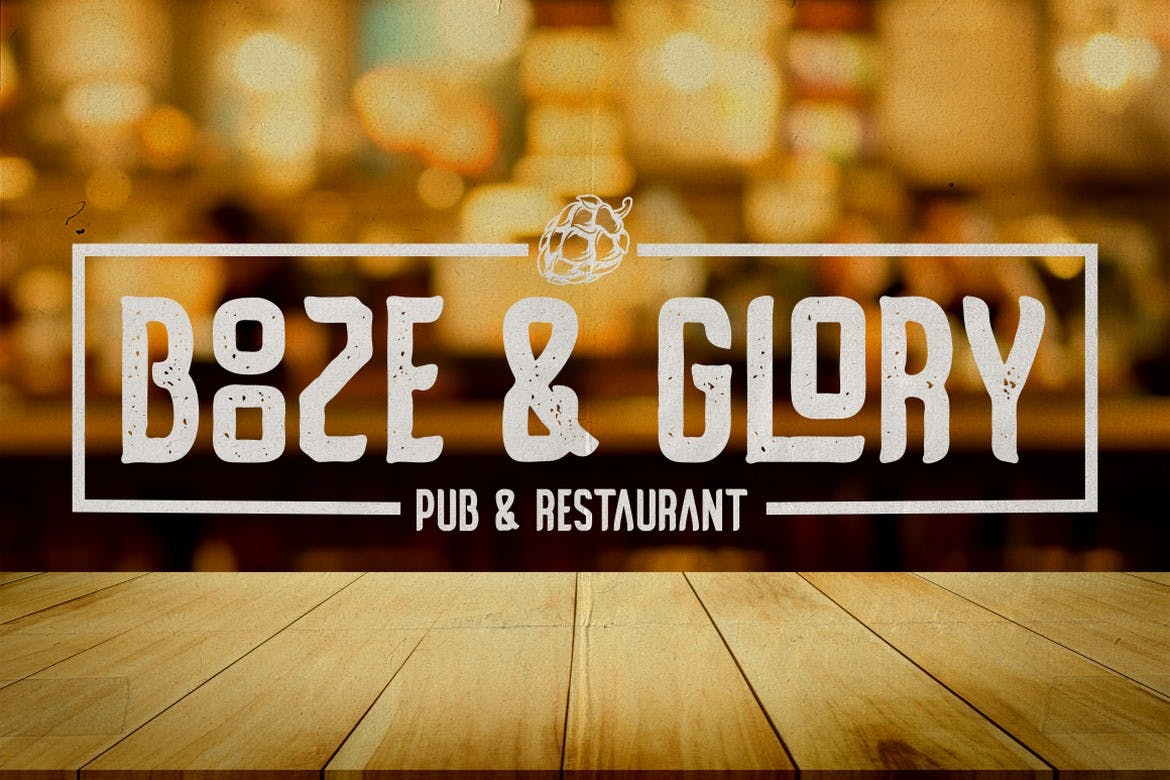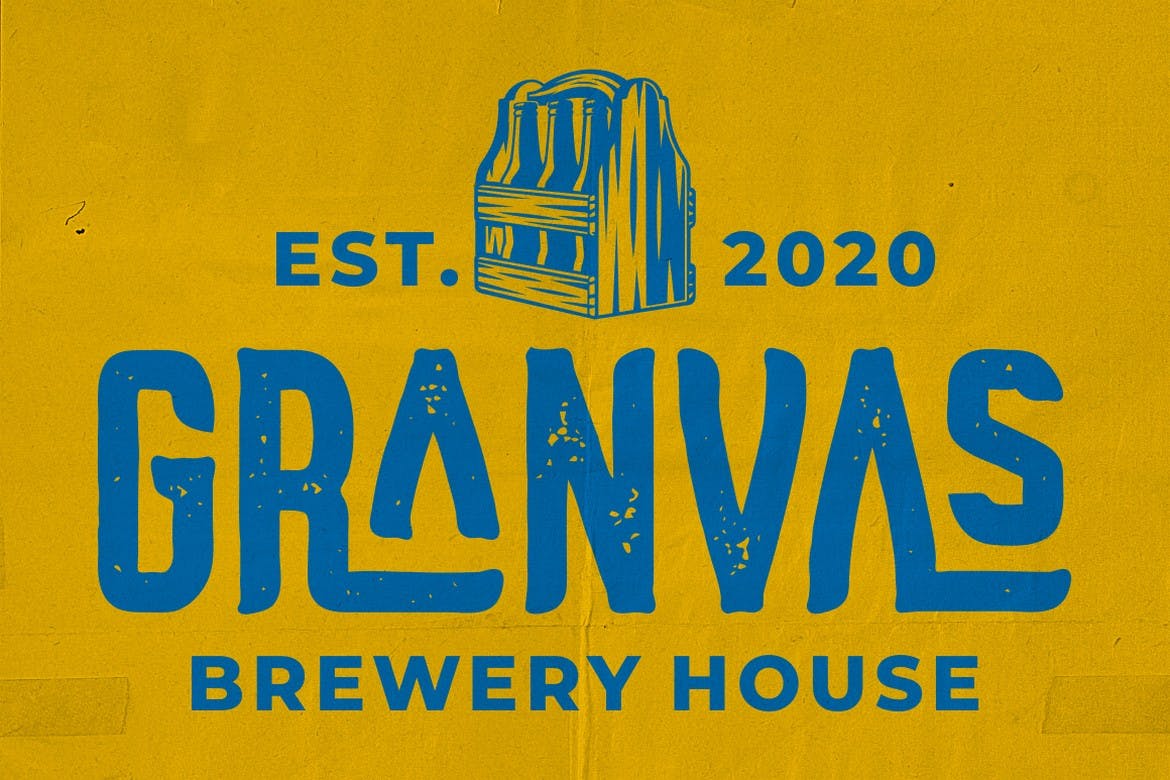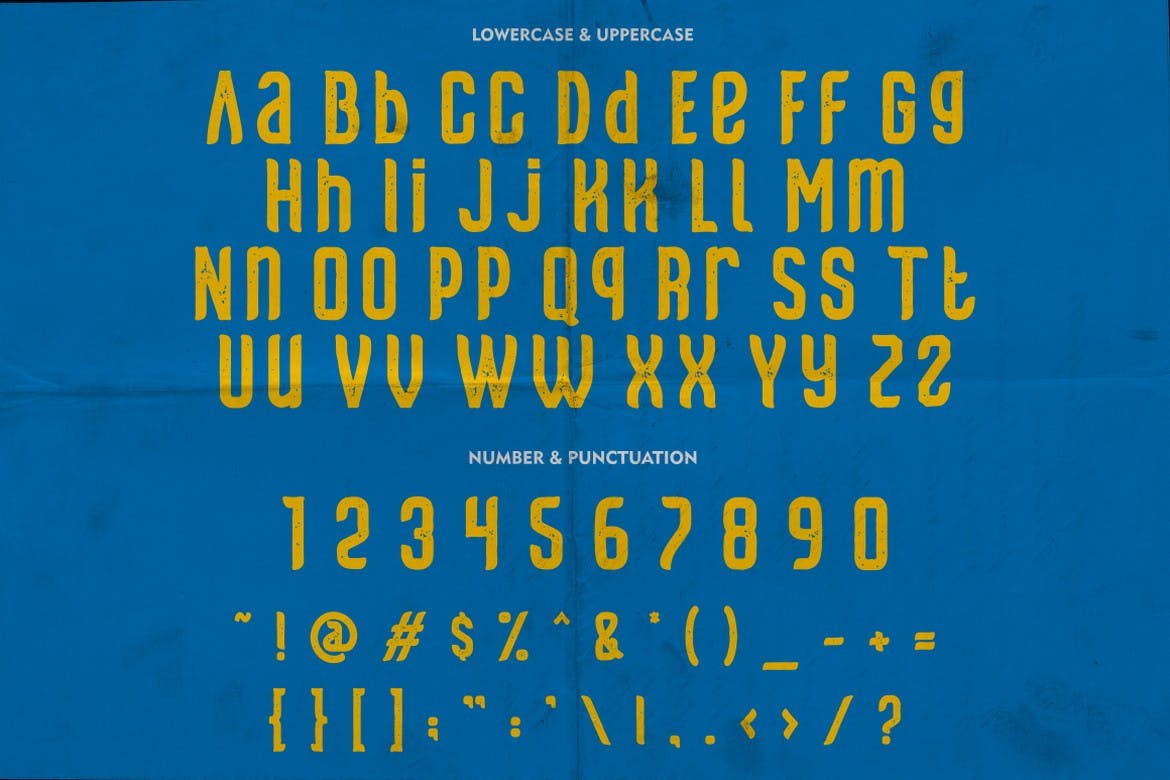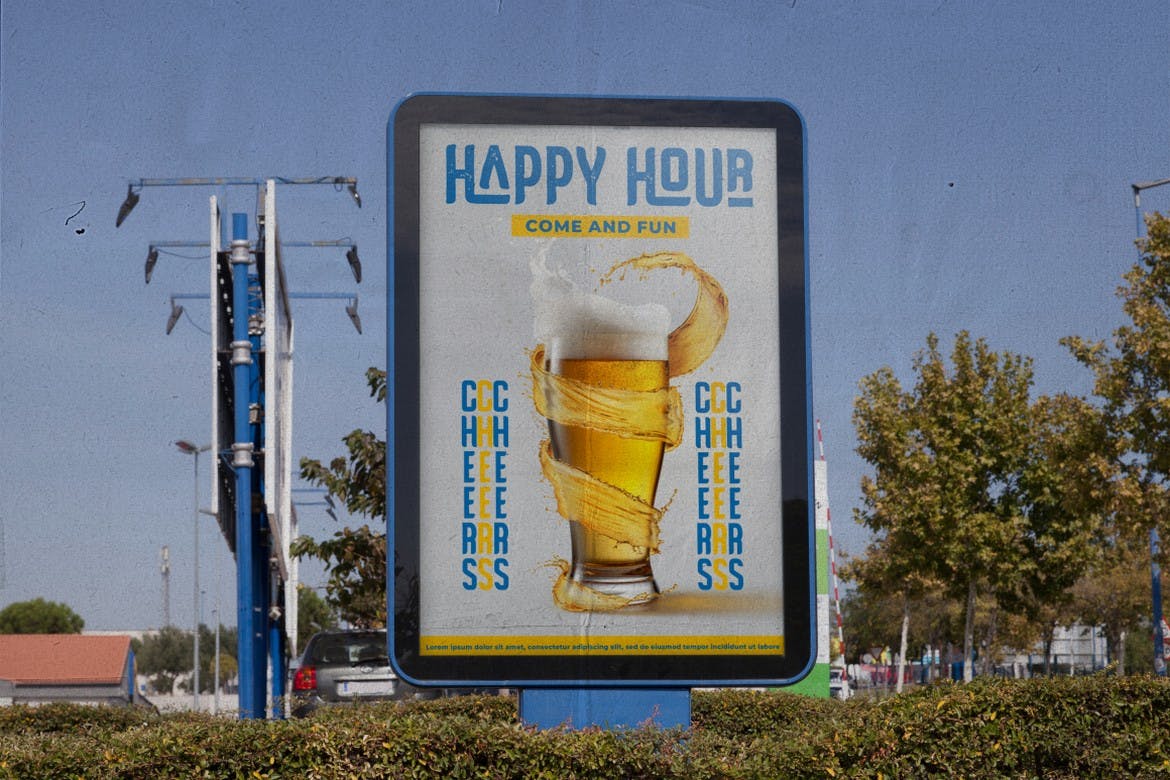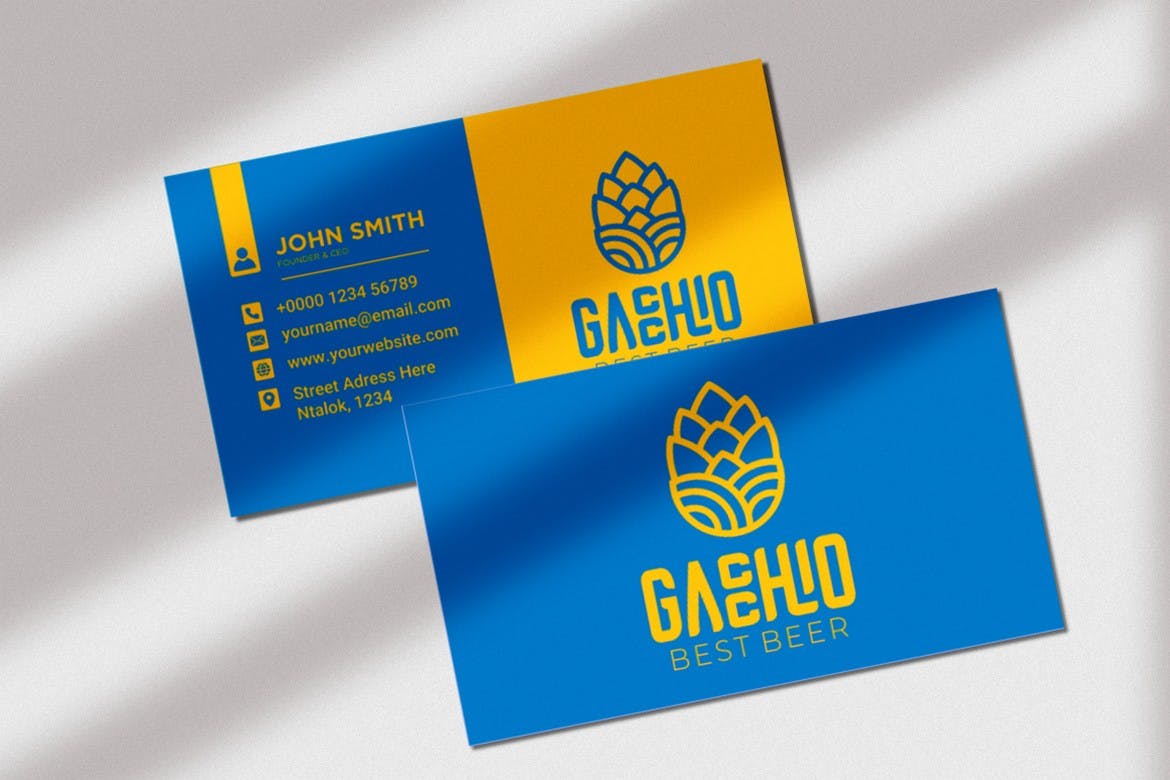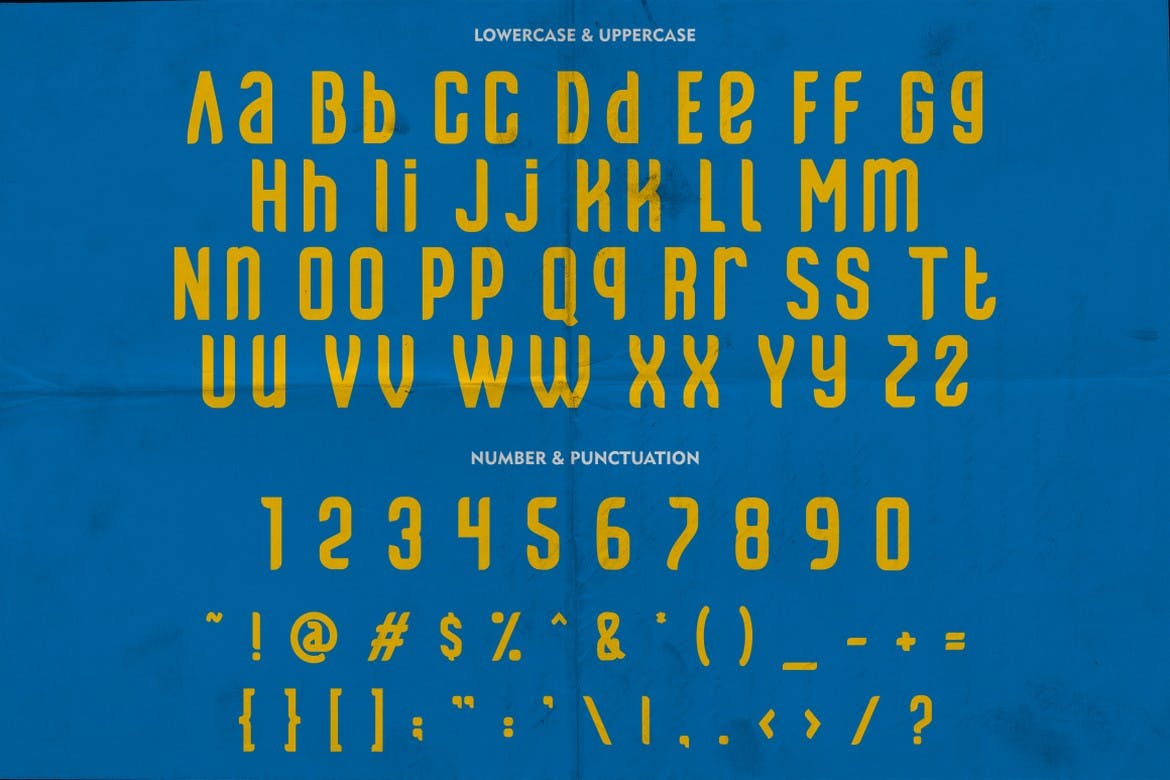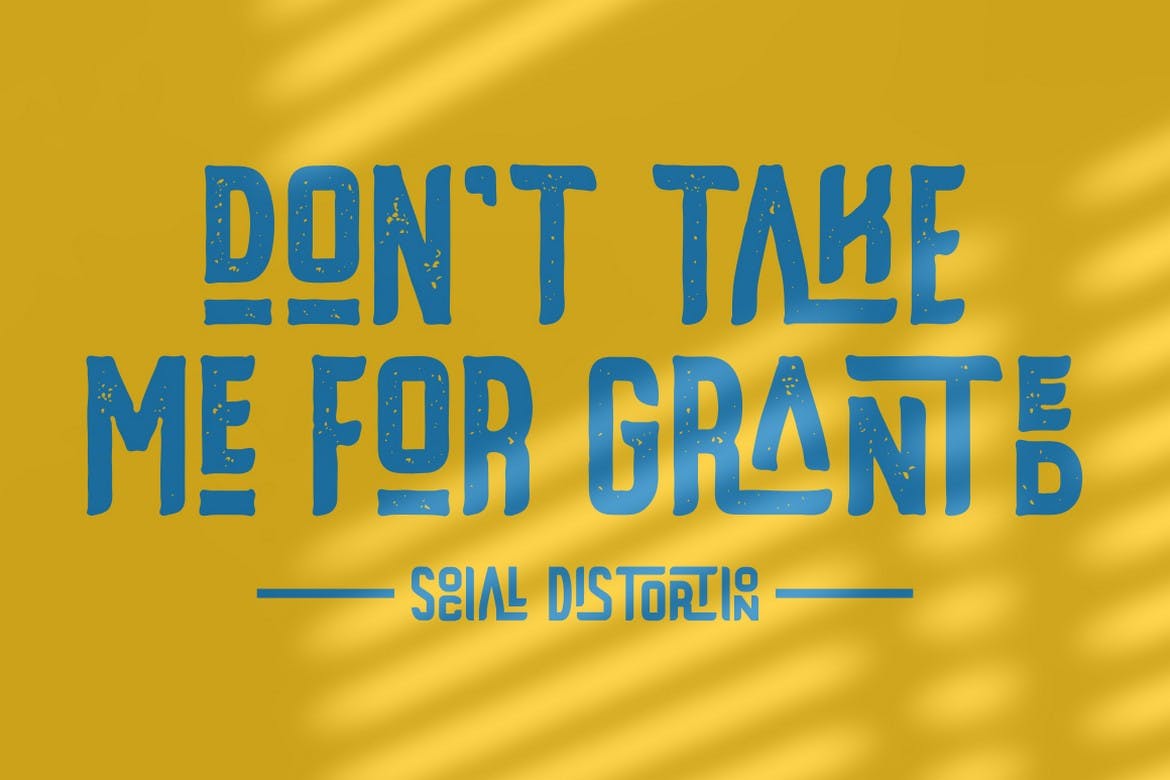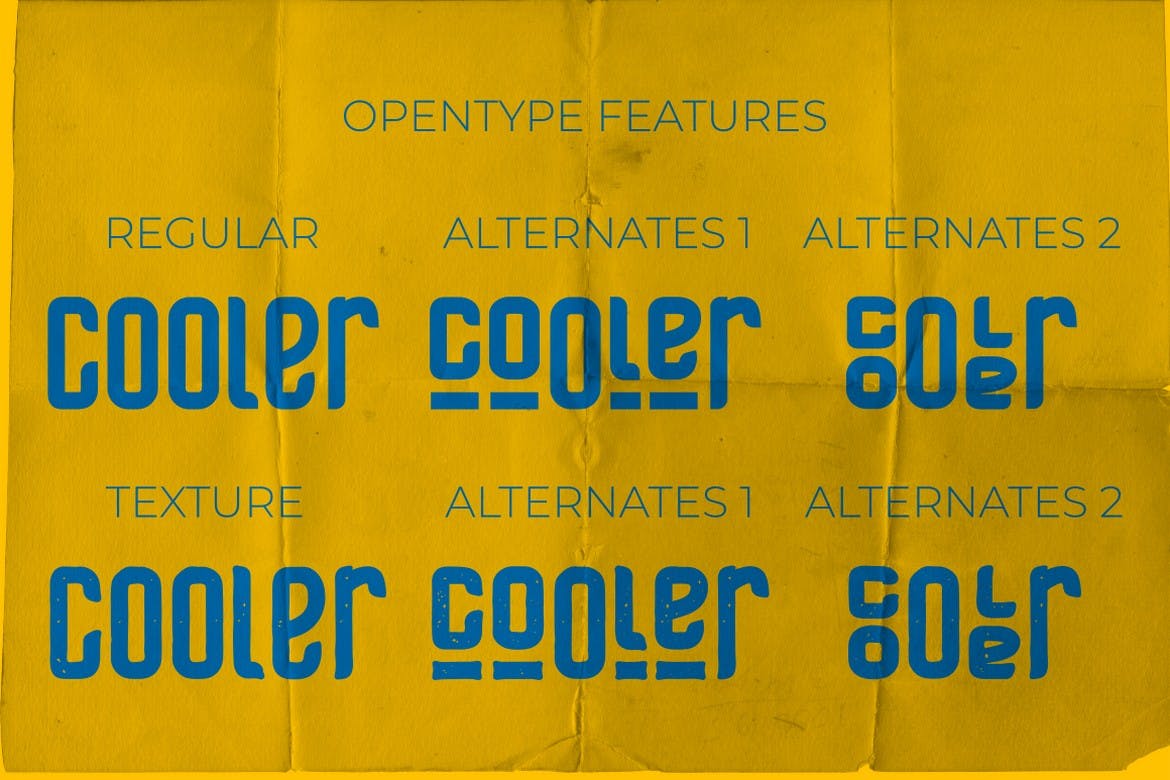
فونت لوگو راورا
فونت راورا با الهام از سبک اروپایی طراحی شده و تنها فونتی است که اشکال و سبکهایی دارد که به طور دقیق با حروف اروپایی مطابقت دارد. این فونت به راحتی خوانده میشود و میتواند در تمام رسانهها مورد استفاده قرار گیرد و همه میتوانند بدون استثنا از آن استفاده کنند.
فونت راورا برای پروژههای شما مانند لوگو، دعوتنامههای عروسی، برندینگ، صفحات فرود، پوسترها، عناوین، کارتهای تبریک، کارتهای دعوت، رسانههای اجتماعی، هنرهای دستی، نقل قول و موارد دیگر مناسب است.